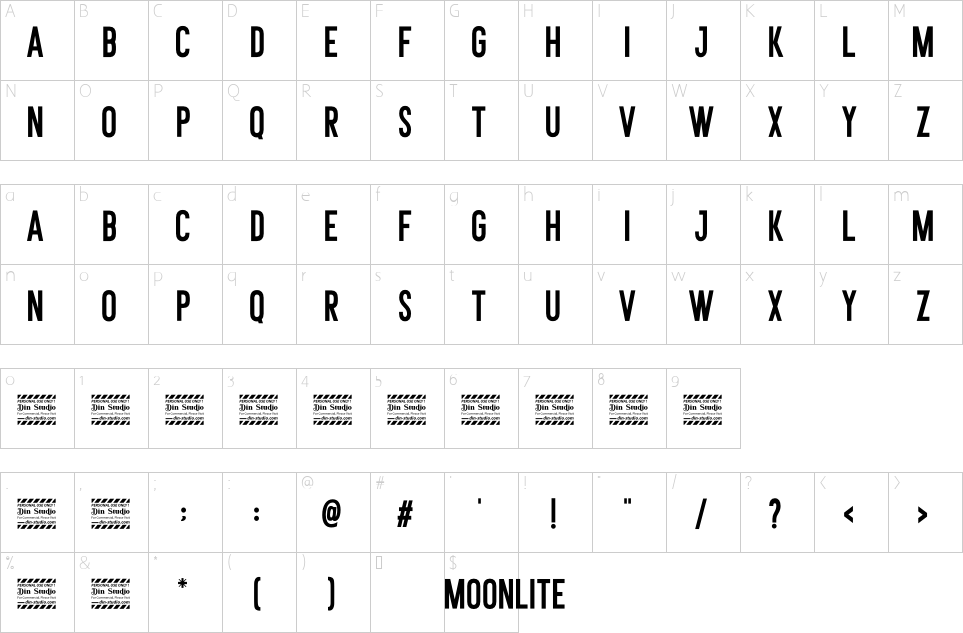
A fonte ‘Moonlite Font | 1001 Free Fonts’ é uma opção perfeita para aqueles buscando um estilo elegante e sofisticado para seu trabalho. Desenvolvida pela Din Studio, esta fonte é ideal para aplicativos e websites, adicionando um toque de modernidade sem perder a elegância. Com sua simplicidade e beleza, a ‘Moonlite Font’ é uma escolha inteligente para designers em busca de uma fonte neutra e versátil. Esta é uma fonte ideal para textos de layout, gráficos e materiais de marketing. Com um design minimalista, ela ajuda a destacar o conteúdo sem atrapalhar a sua presença. Se você está procurando uma fonte gráfica de alta qualidade para seu projeto, ‘Moonlite Font’ é definitivamente algo a considerar. Esta fonte já foi baixada 14.638 vezes, uma indicação de sua popularidade entre designers e criadores de conteúdo.